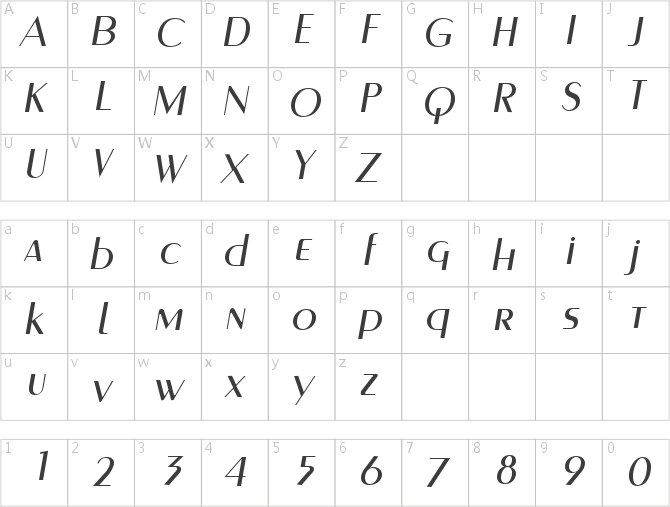
PenultimateLightItal 詳情頁
PenultimateLightItal字體字庫是一款讓人賞心悅目、百看不厭的英文字體,適合各類廣告和產(chǎn)品包裝設(shè)計(jì)應(yīng)用,字體大小0.04MB,格式為ttf字體,上傳用戶是我,Dirac,作者/版權(quán)方為未知